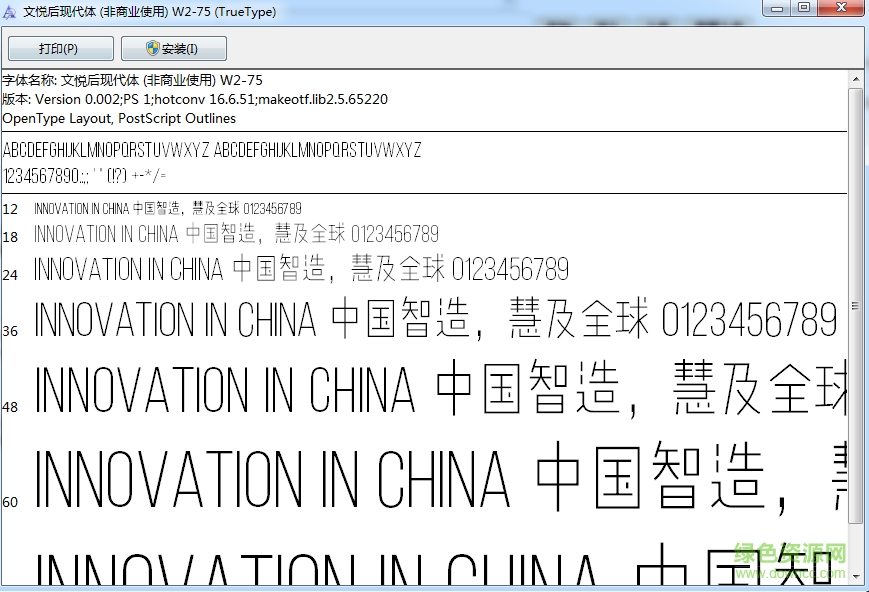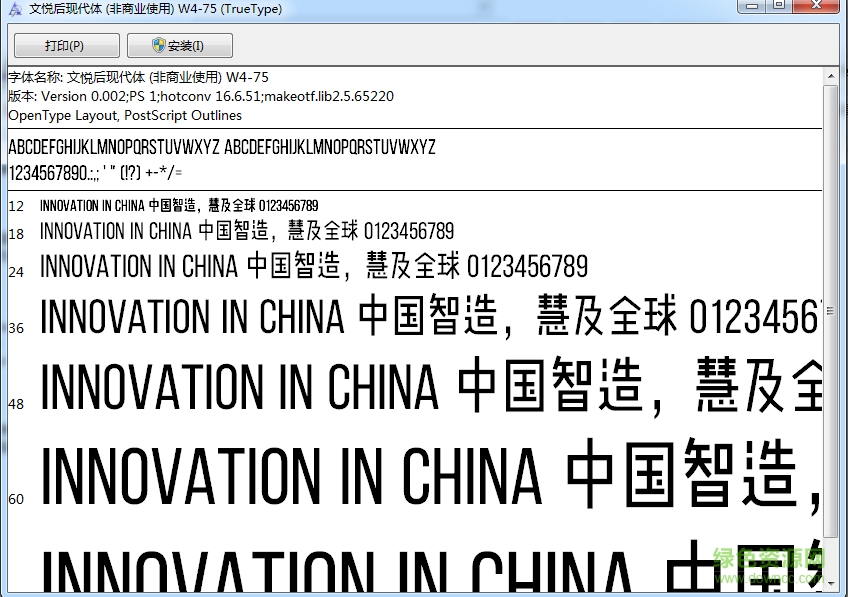
文悅后現(xiàn)代體是一款充滿時(shí)尚元素的文悅字體,構(gòu)造簡(jiǎn)約大方,有著美術(shù)視覺觀感和舒適體驗(yàn),讓你的創(chuàng)作打印更顯獨(dú)特魅力,綠色資源網(wǎng)誠(chéng)意推薦!
「文悅后現(xiàn)代體(系列)」采用 2013 年國(guó)務(wù)院公布、教育部、國(guó)家語言文字工作委員會(huì)組織制定的《通用規(guī)范漢字表》。
《通用規(guī)范漢字表》是一份較 GB2312-80、GB12345-90 更加適宜現(xiàn)代社會(huì)使用的常用字字符集標(biāo)準(zhǔn)。